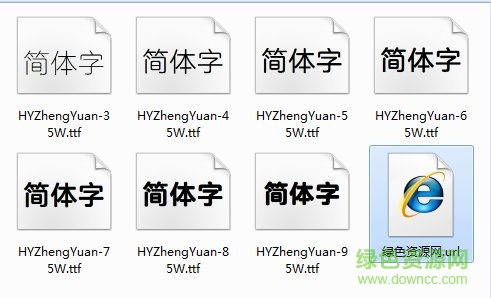
漢儀正圓(共7款)
漢儀正圓字體打包文件里包含了7款免費的字體資源,有漢儀正圓45w、漢儀正圓55w等字體文件。這一個系列的字體外形規(guī)范、圓潤!在很多個設計領域都比較受歡迎!歡迎大家來綠色資源網(wǎng)下載使用。
漢儀正圓字體筆畫粗細一致,字體看起來很端莊大氣。無論是設計商標還是廣告都是個不錯的選擇!